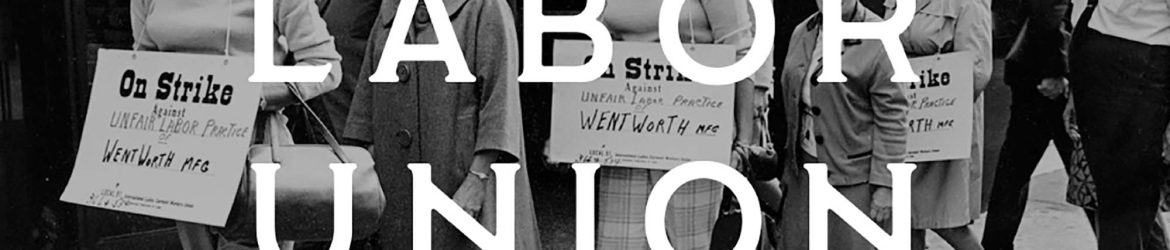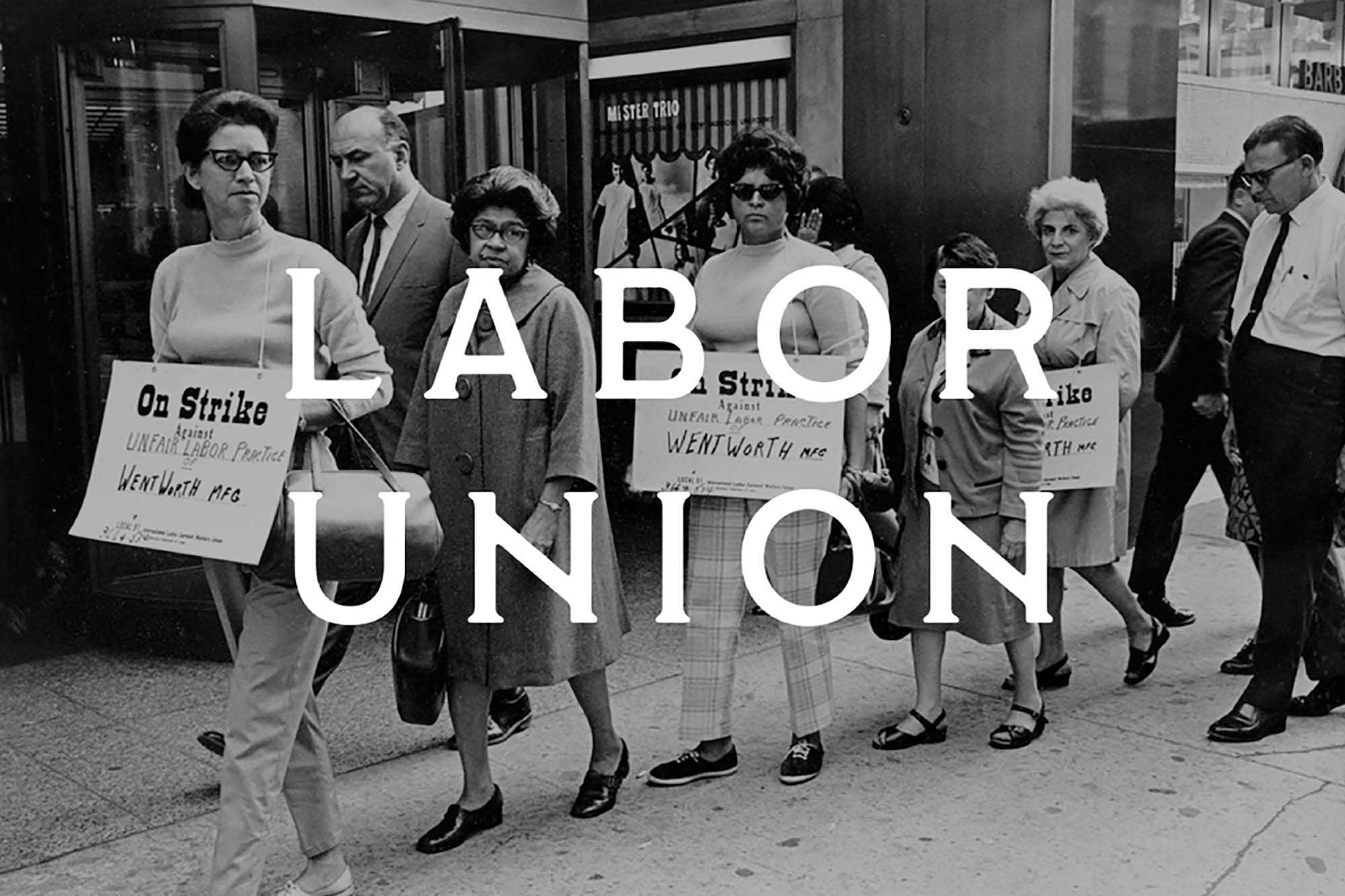
Labor Union Serif Font
Aqui está a descrição conforme solicitado, envolvente e natural, em duas parágrafos curtos, para a página de download do recurso gráfico ‘Labor Union Serif Font’, categoria Mockups: No mundo vibrante e diversificado do design gráfico, o ‘Labor Union Serif Font’ é uma escolha perfeita para quem valoriza a estética e a funcionalidade de um bom tipo. Especialmente apreciado por designers e artistas visuais, este font é tão versátil quanto elegante, pronto para moldar textos de forma impecável em qualquer projeto. Seja para comunicar uma mensagem clara e precisa, ou para criar um design de primeira classe, o ‘Labor Union Serif Font’ está aqui para ajudar a fazer a diferença. Sempre atento à sua funcionalidade e à sua importância estética, este recurso gráfico é uma escolha segura para quem busca qualidade em cada projeto.